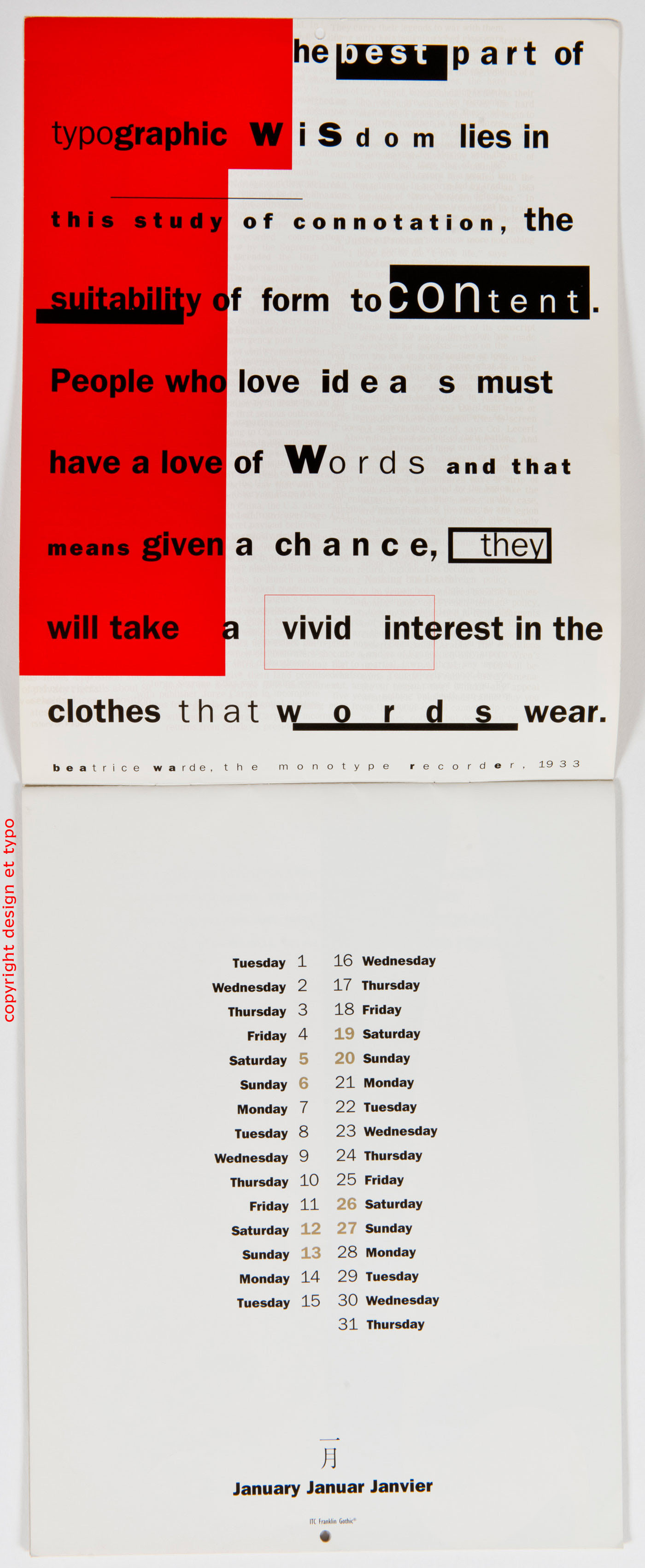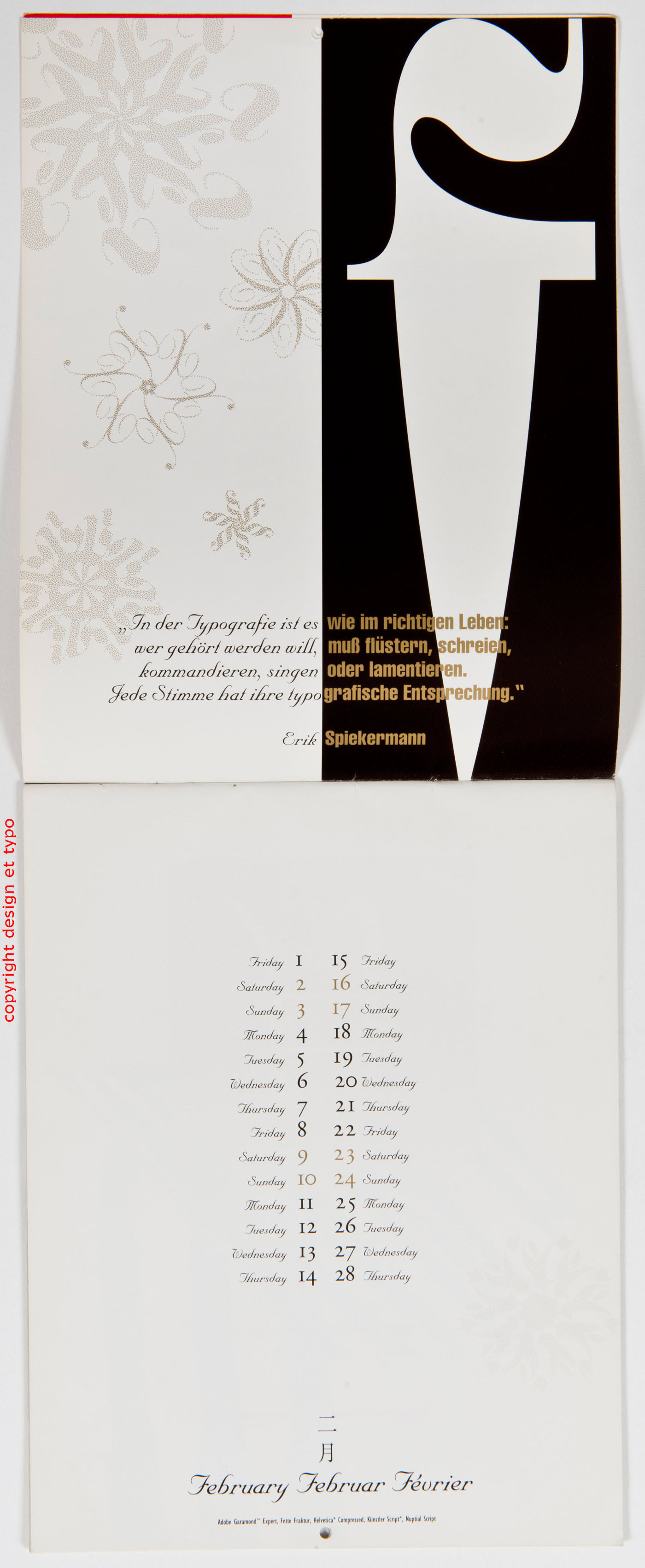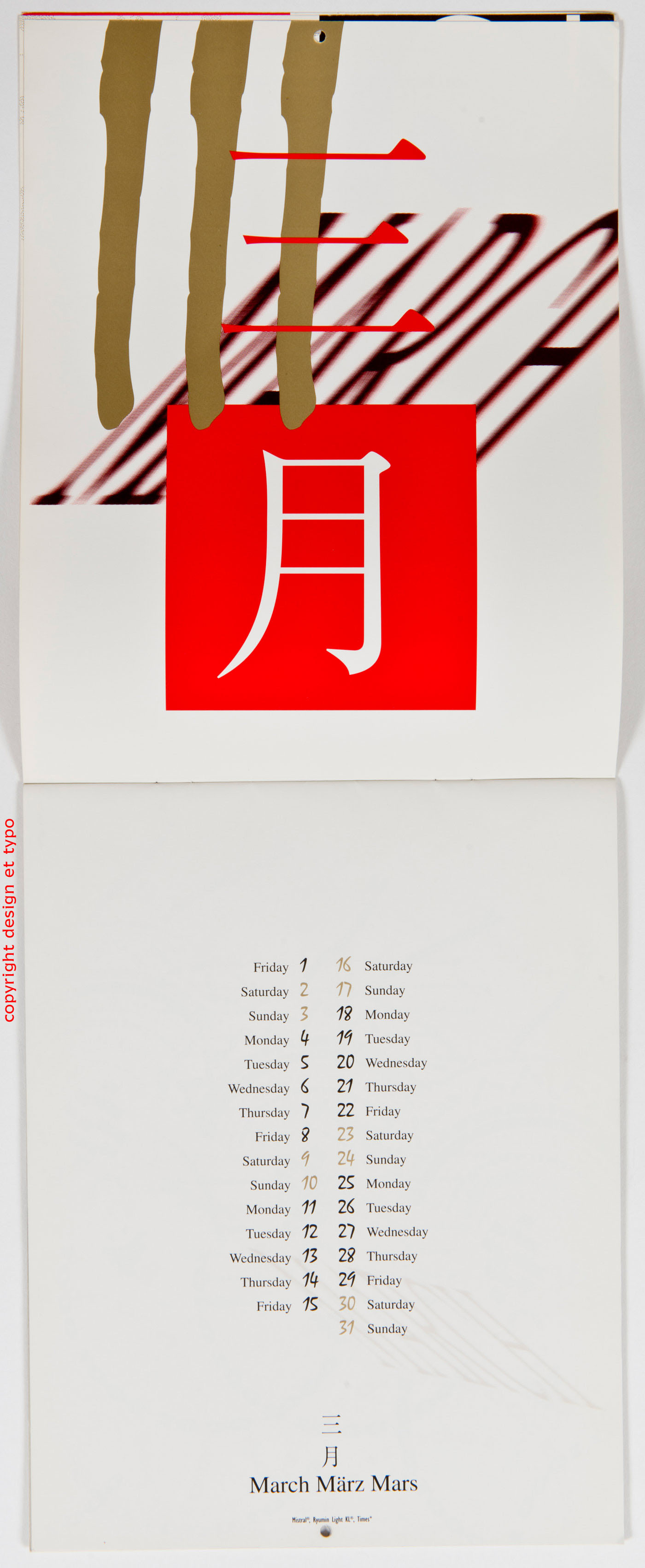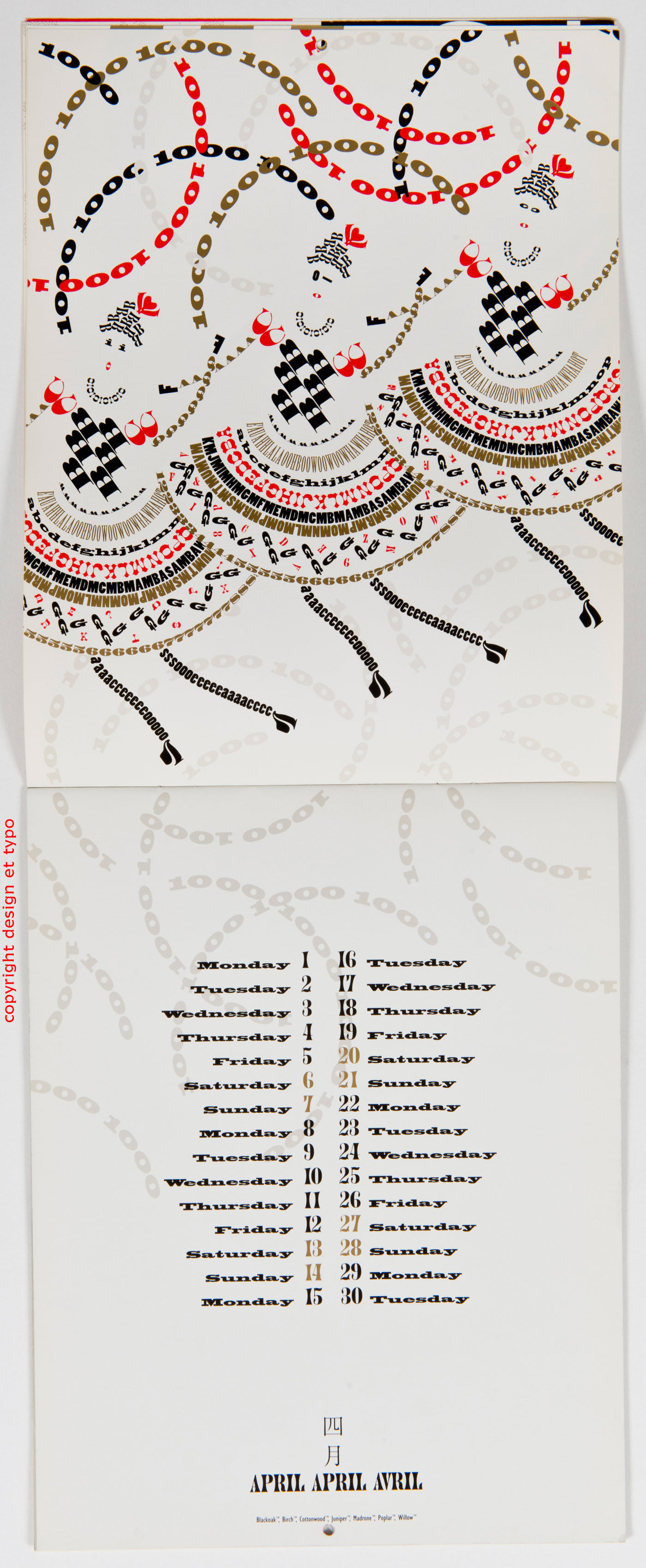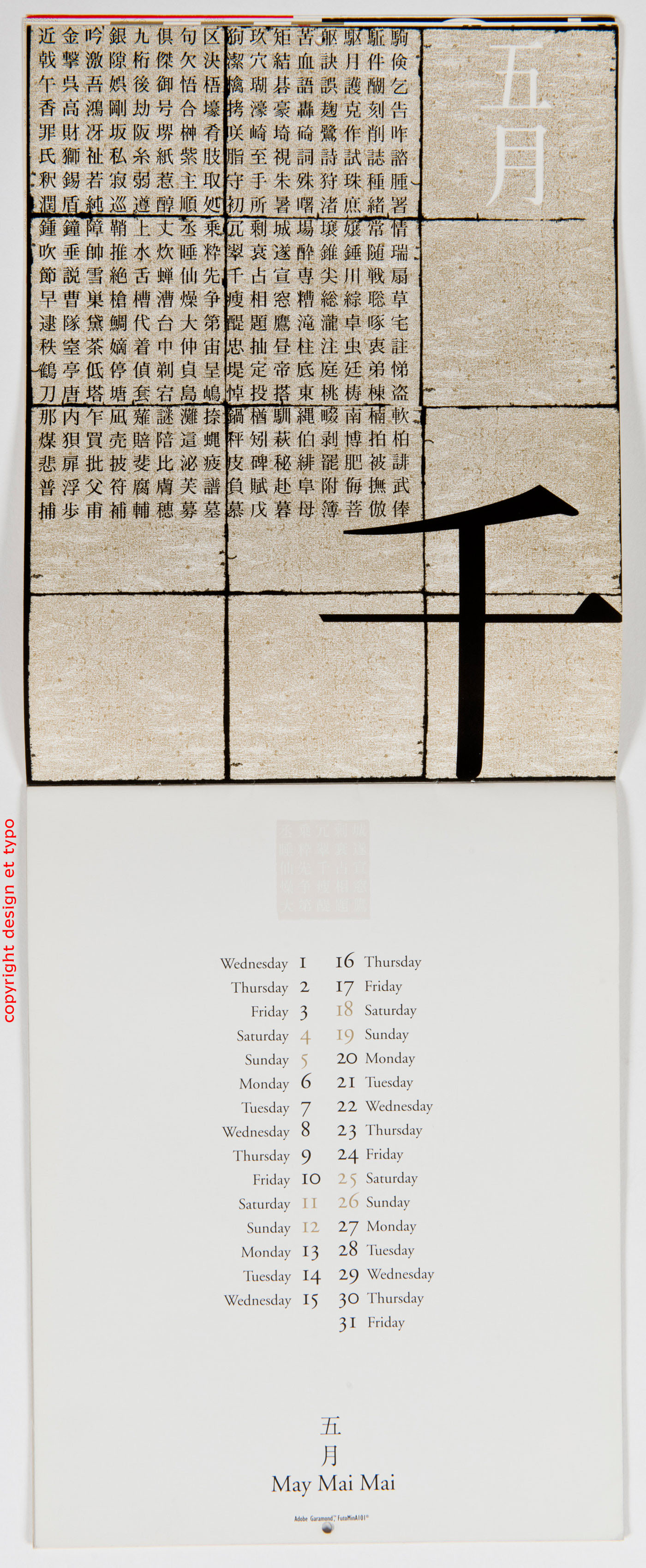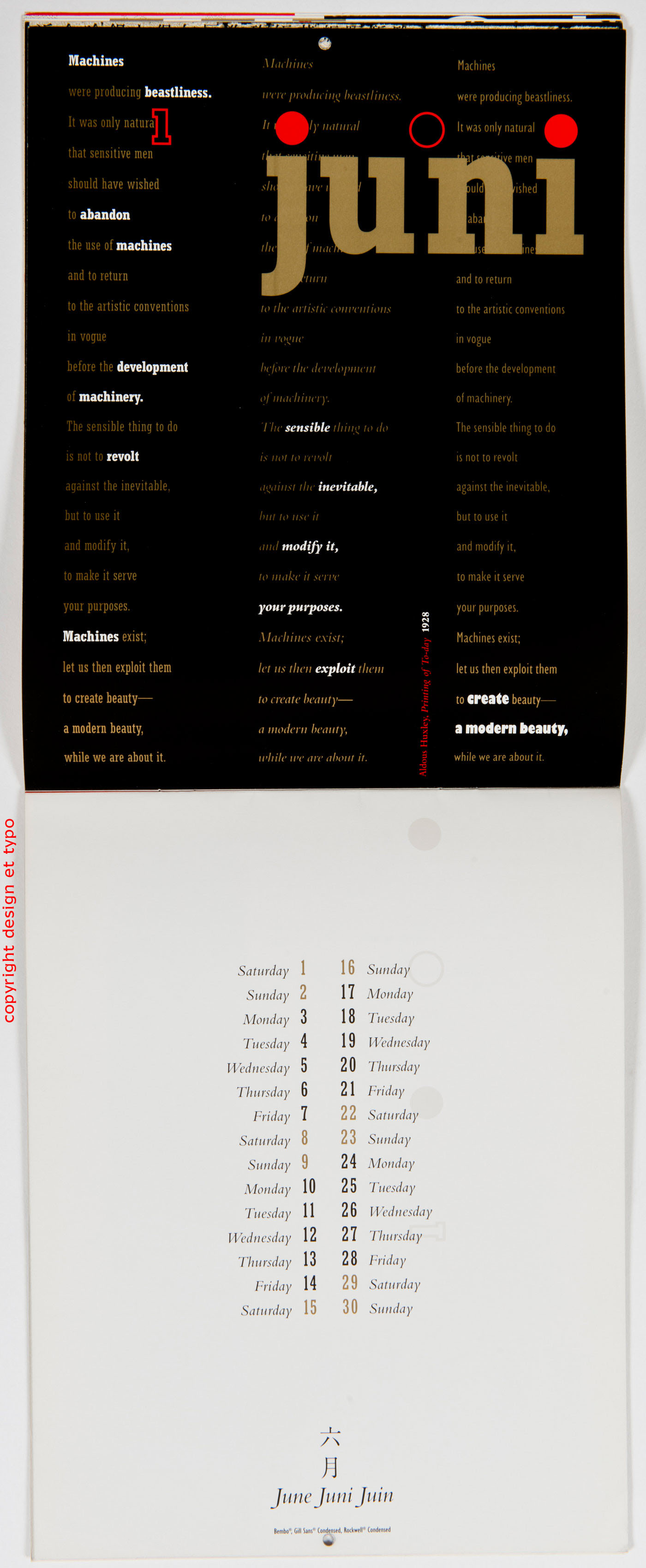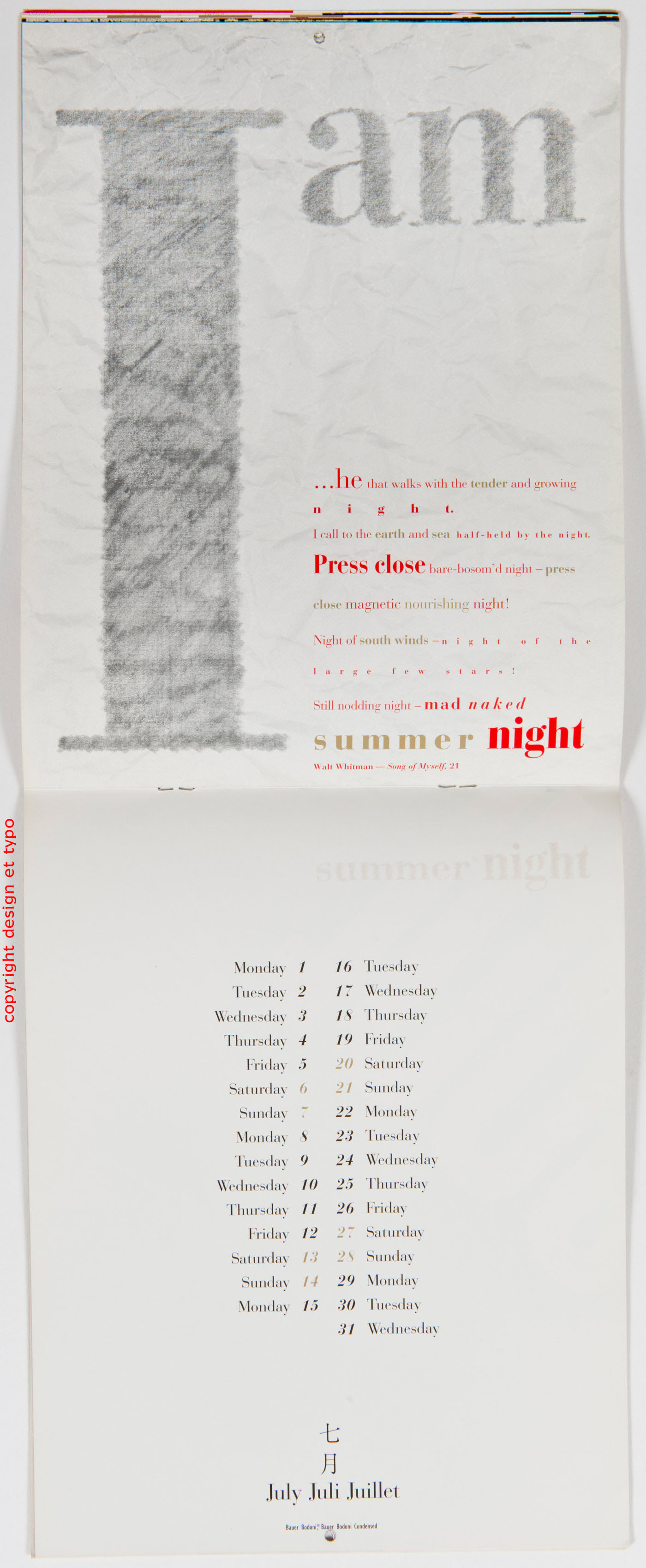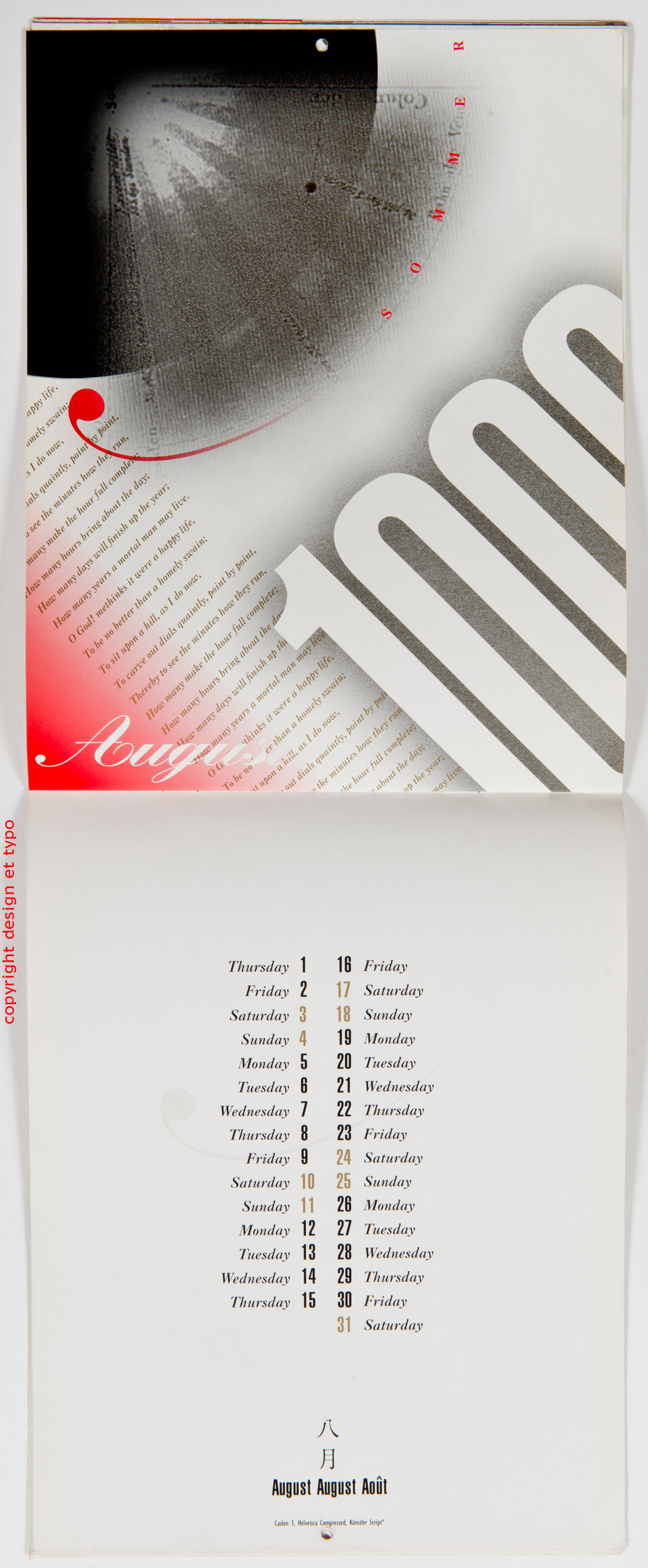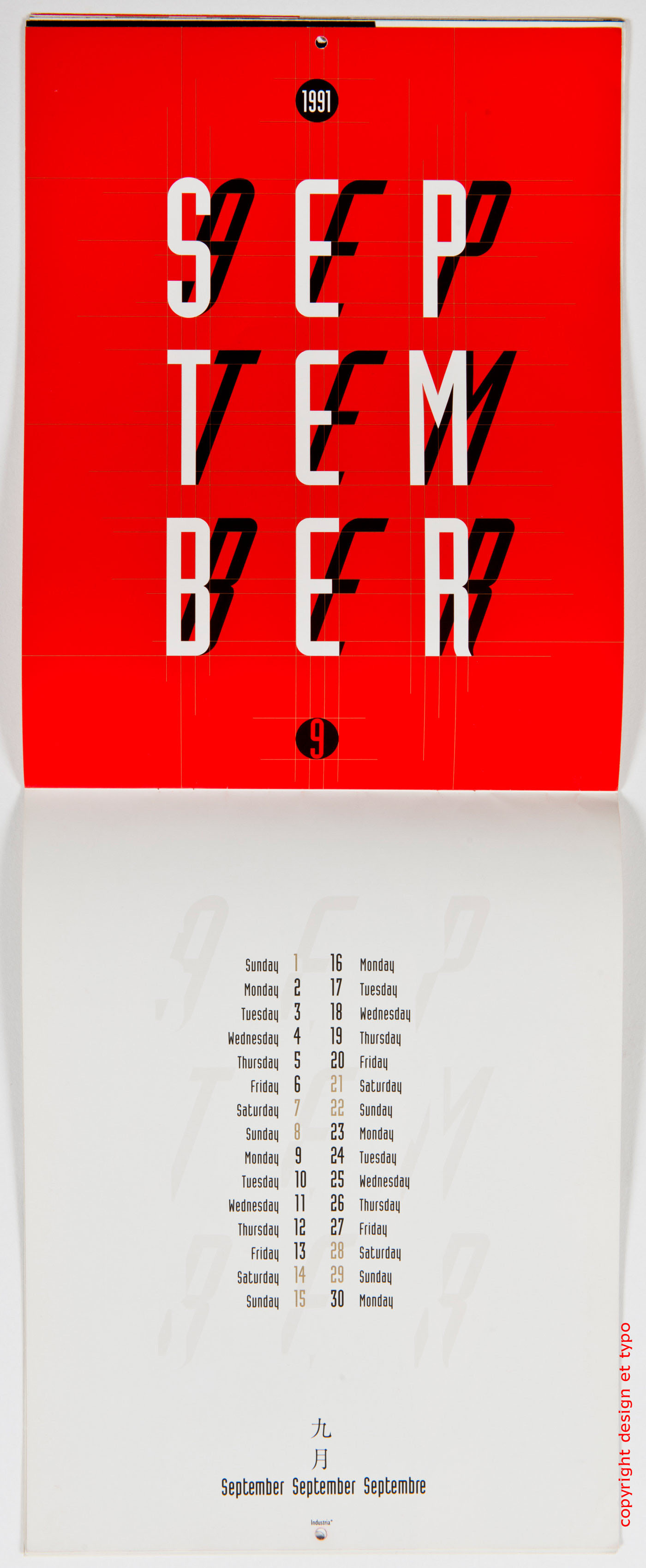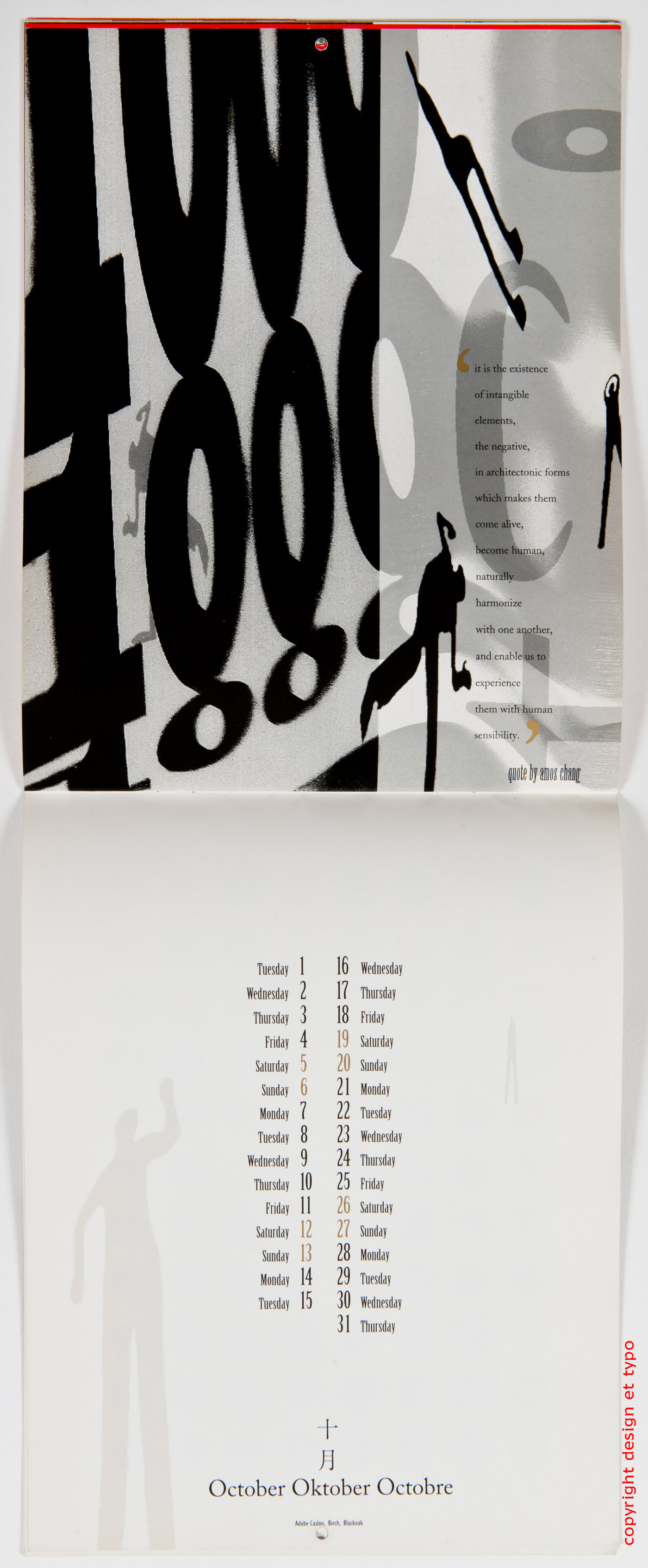
Calendrier d’Adobe en 1991 | Ça n’était pas la fin du Monde, mais les débuts du Postscript©
Nous sommes tout à fait au début de l’ère industrielle du ©PostScript, langage mis au point par les équipes de John Warnock et dont ce dernier va abandonner tous les droits en septembre 1989 (annonce faite au Seybold Report Annual à San Francisco).
Le monde redessiné par les courbes de Bézier pourrions-nous dire, avant que de sombrer dans une fin du monde que d’aucuns nous annoncent pour dans… 5 milliards d’années. Voilà une nouvelle qui devrait sinon vous rassurer éloigner de vous les affres d’une angoisse existentielle inutiles et fatigantes.
Et voici déjà une petite œuvre graphique, qui montre la versatilité des technologies vectorielles qui autorisent tous les effets visuels que l’on connait désormais au travers de nos logiciels Illustrator, Photoshop ou InDesign. Mais si la technologie explose désormais, il n’en demeure pas moins que la firme Adobe soignait comme encore aujourd’hui la créativité visuelle et ici la rigueur typographique. Enjoy et n’hésitez pas à cliquer pour zoomer sur les pages. peter gabor | directeur d’e-artsup.